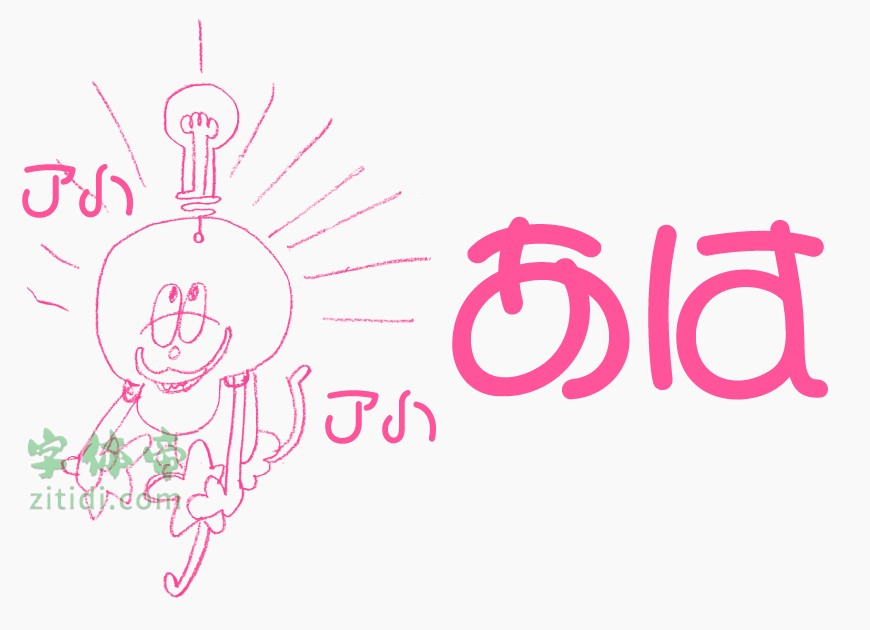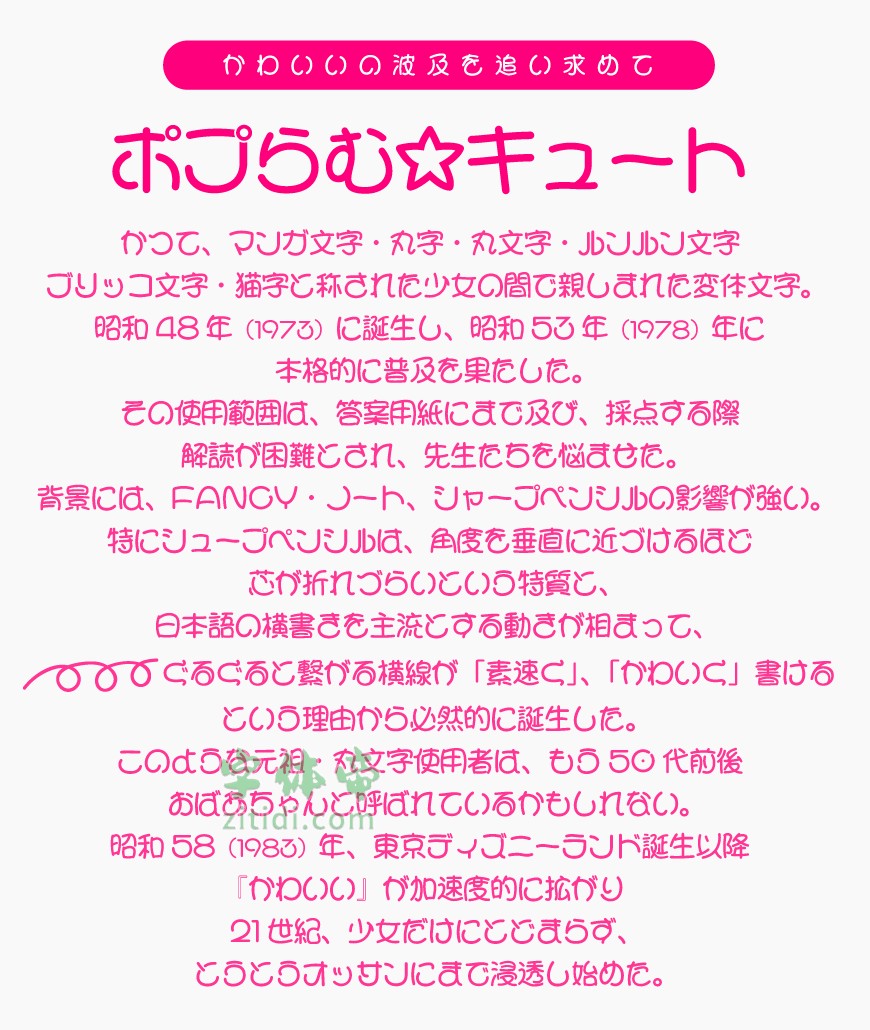
这是一款来自日本的非常可爱的字体, 「 卡哇伊可爱体 」(日文名:ポプらむ☆キュート ) 。支持的汉字不算特别多,这是比较可惜的。但是其可爱的字型还是让人爱不惜手,喜欢这套字体的朋友们可以一试哦。说不定刚好有你想要的字体呢。
「 卡哇伊可爱体 」 收录汉字约3200个 (JIS第1水准2965字,第2水准260字)
“卡哇伊可爱体”是一款书写很新颖的字体,字体大方,适合各种设计作品使用!欢迎下载!